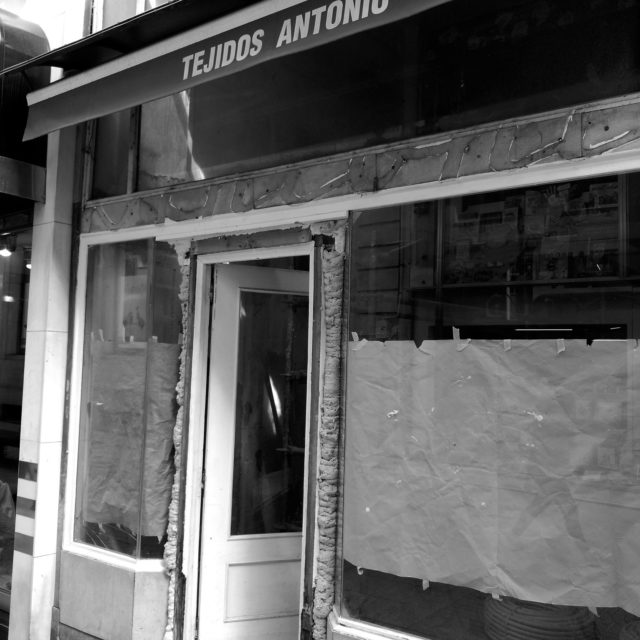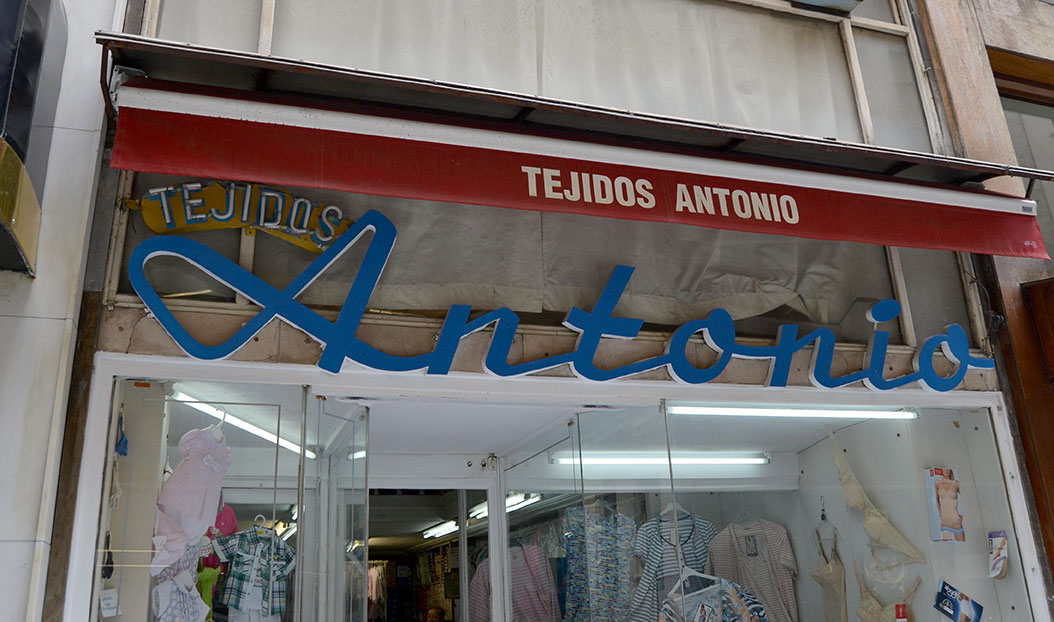
Tejidos Antonio
Y los cambios en la fisonomía de las calles sigue su curso. Aunque de tres tiendas que fueron abiertas bajo «Tejidos Antonio» sólo quede una abierta. Eso no quita que un rótulo hecho en madera tan particular haya desaparecido de la tienda original, abierta en 1944 y que aguantó hasta hace muy poco a pie de calle {Ver ficha}